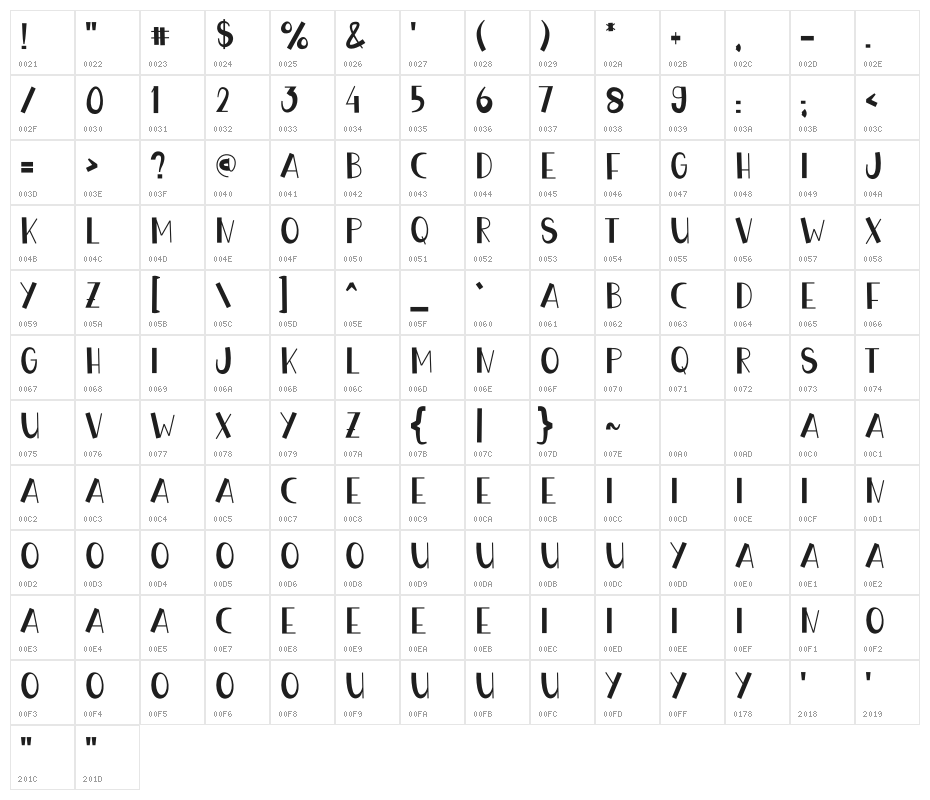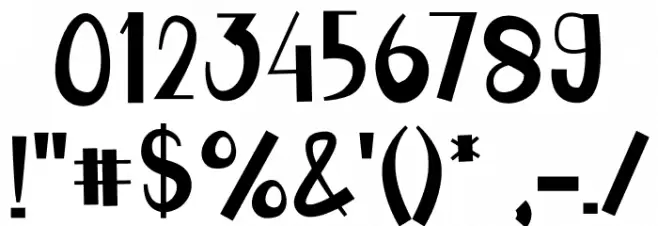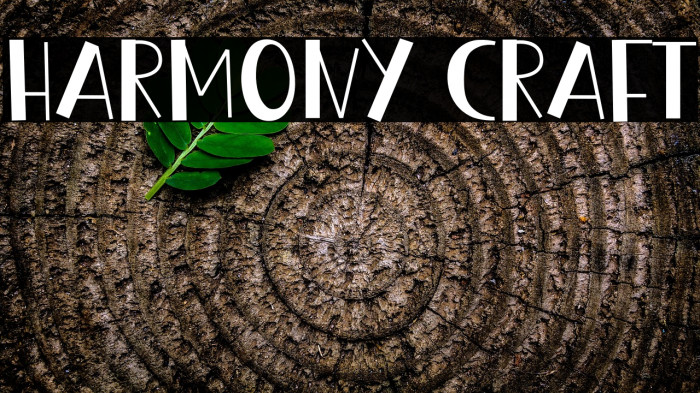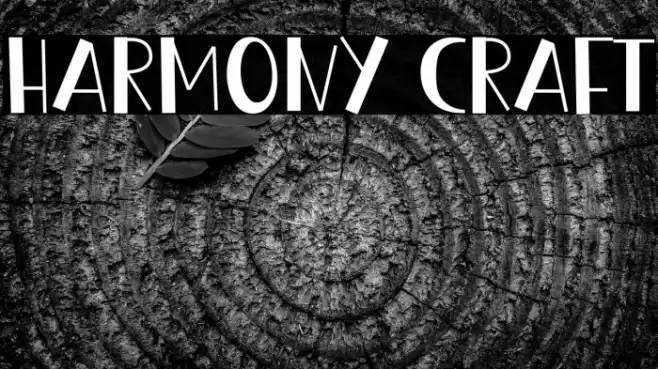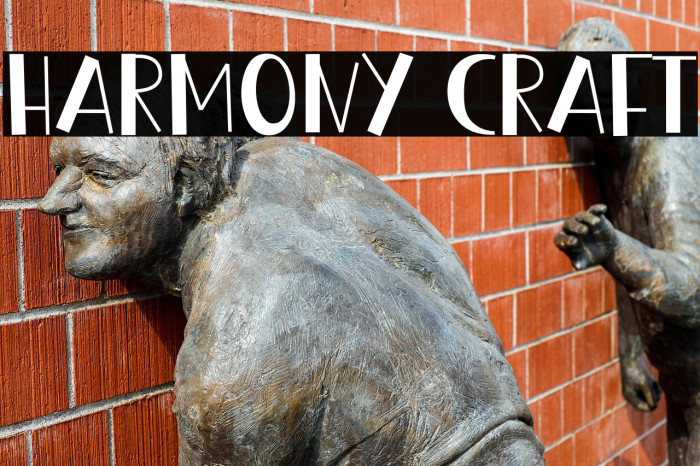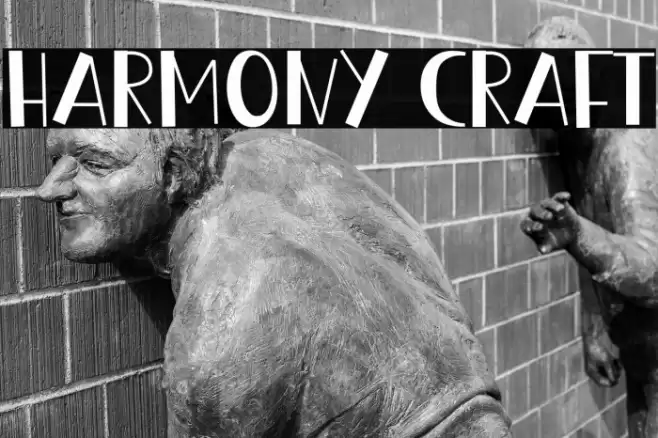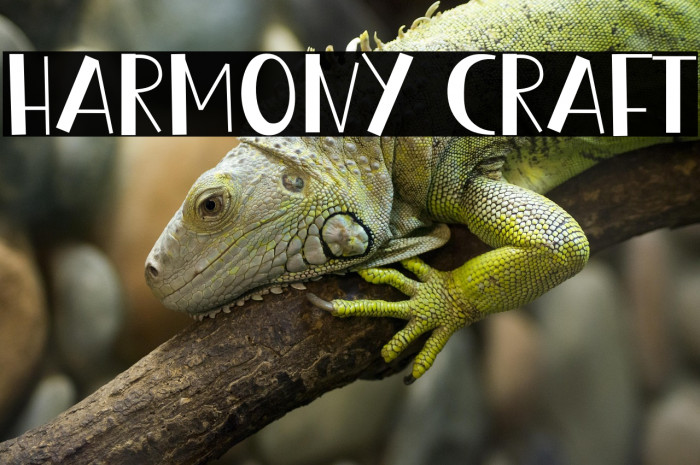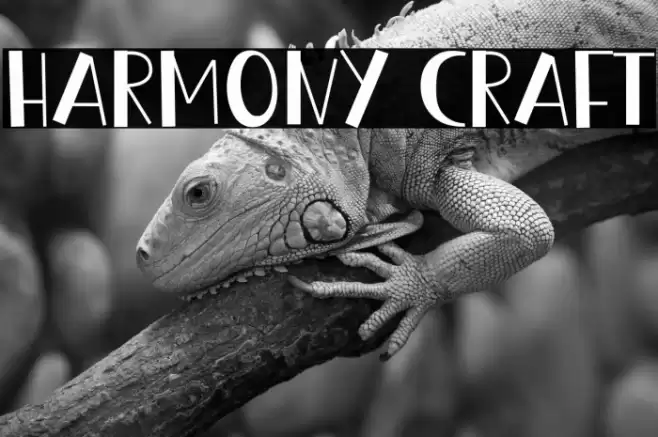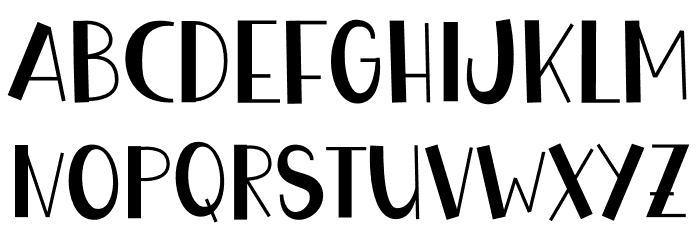
Harmony Craft Font
| 名前 | Harmony Craft |
| フォントファミリー | Harmony Craft |
| カテゴリ | Cartoon |
| 全体的なスタイル | Playful, Artistic |
| おすすめプロジェクト | Ideal for children's books, creative posters, playful branding, and artistic invitations. |
| 作者 | Fonts by Letter Art Studio |